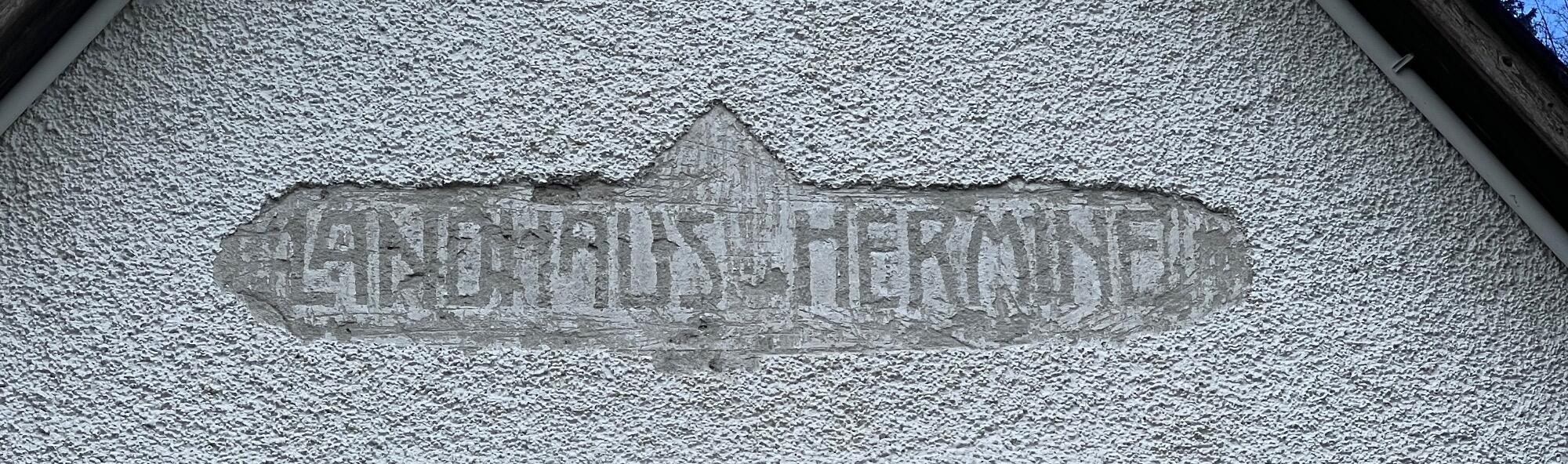
Vielleicht Jugendstil?
Möchte den Schriftzug am Haus renovieren, was für eine Schrift ist das?
Hallo @Hermi, das ist Jugendstil-Lettering und keine Satzschrift. Eine originalgetreue Renovierung lässt du im Idealfall durch einen Lettering-erfahrenen Designer erledigen, der den Schriftzug schnell digital nachzeichnen kann. Hier im Forum gibt’s einige davon (du kannst mir auch eine Direktnachricht schreiben, wenn du willst).
Wenn du die Renovierung nur lose ans Original anlehnen und dafür eine Satzschrift verwenden willst, kommst du mit David Jonathan Ross’ Polliwog von 2019 (basierend  auf Lettering des Jugendstilkünstlers Max Josef Gradl) schon sehr nah heran. Die Polliwog ist allerdings fetter und einige der Buchstabenformen unterscheiden sich; auch ein Ineinandergreifen von /L und /A wie in »LANDHAUS« bekommst du dort nicht »out of the box«.
Guten Morgen, D2c, danke für die kompetente Antwort, denke dass die Renovierung nicht einfach wird, Maler haben abgesagt. Kennst du jemand für die Renovierung in Österreich? Ich möchte schon gerne das Original erhalten. Mir wurde angeboten, darüber verputzen und dann eine annähernde Schriftschablone, die aufgeklebt wird.
das klingt ja schon mal ganz gut, wenn das technisch/handwerklich gut draufgepinselt wird. den schriftzug sauber nachbauen ist kein problem.
Wenn die Daten für den Schablonenplot geliefert werden, sollte damit eigentlich jeder Malermeister zurechtkommen. Frag vielleicht noch mal an, ob sie es doch machen, wenn sich ein externer Designer um die Vektorisierung kümmert.
Das Vorgehen klingt sinnvoll. Einen Betrieb für die malerische Umsetzung in Österreich kenne ich nicht. Bei deinem Partner für die Vektorisierung bist du aber geografisch völlig frei, so lange du ein gutes Foto und ein paar Maße per Mail schicken kannst. Du kannst dein Anliegen dafür zum Beispiel hier in der Börse ausschreiben.
In Österreich gibt es viele gut ausgebildete Fachleute auf diesem Gebiet.
Die zuständige Behörde für Denkmalpflege in Österreich ist das Bundesdenkmalamt. Dort kann man anfragen wer derartige Arbeiten professionell durchführt und ob Förderungsmittel zu erhalten sind.